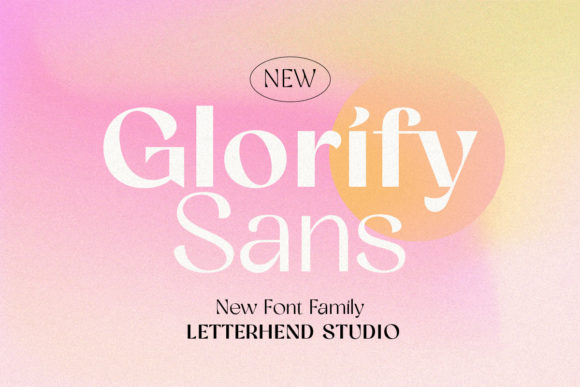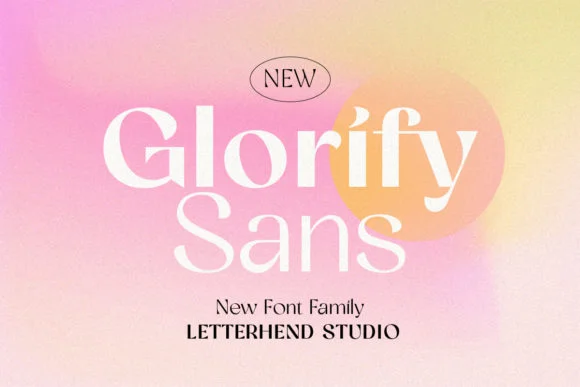
[Creativefabrica] Glorify Font (2021)
Название: Glorify Font (2021)
Glorify
- элегантный и выразительный шрифт с засечками.
Независимо от темы, этот шрифт станет отличным дополнением к вашей библиотеке шрифтов, поскольку он способен возвысить любое творение.